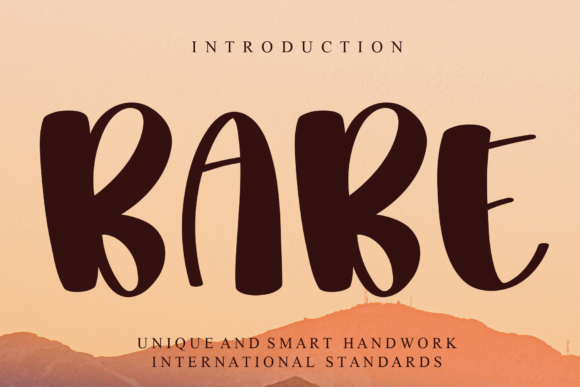
Creativefabrica Babe Font 2021
[Creativefabrica] Babe Font (2021)
Babe - это игривый и современный шрифт.
Этот шрифт с немного неровными символами и дружелюбной атмосферой станет отличным выбором для каждого из ваших будущих проектов!